Что такое кернинг и как он влияет на восприятие текста
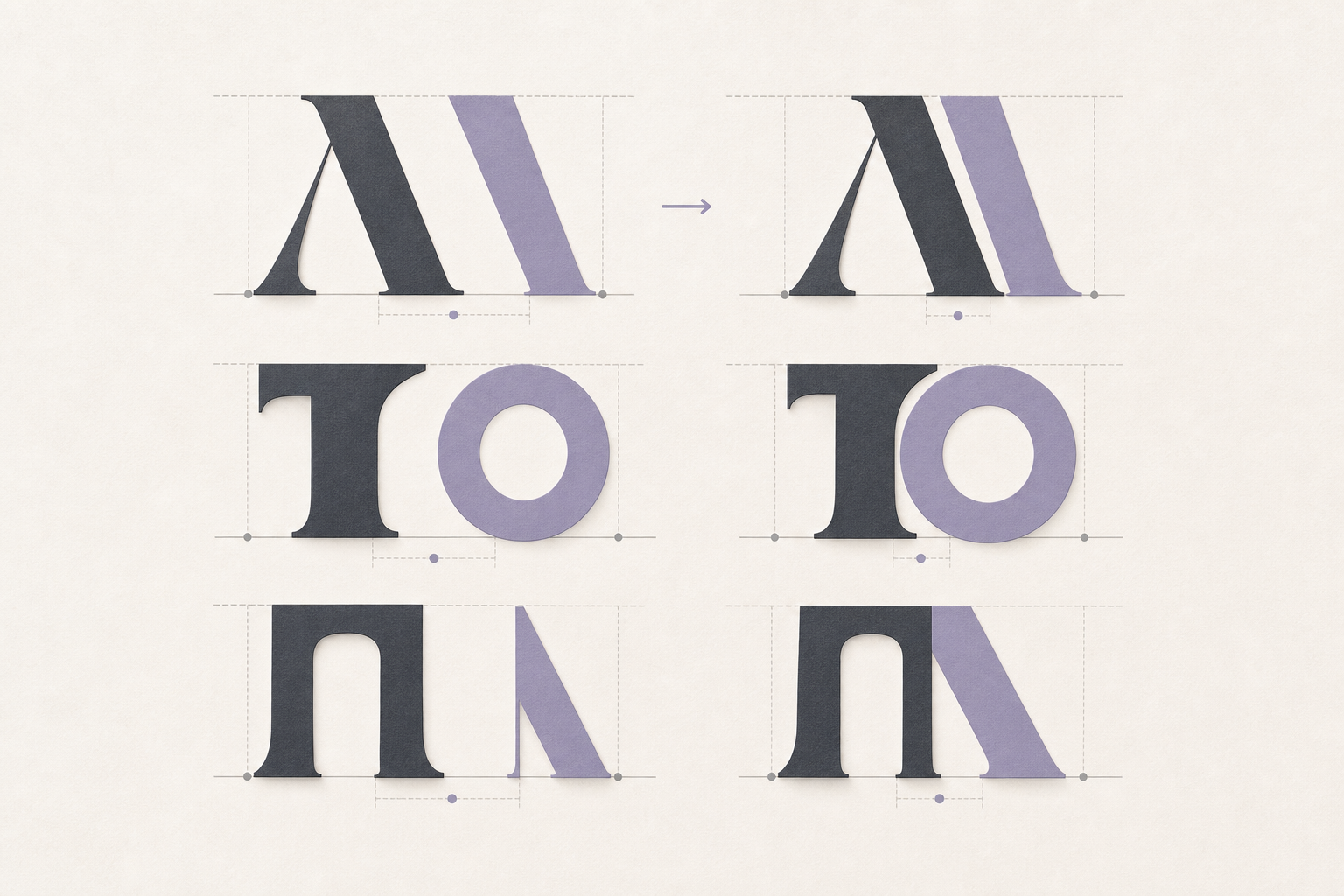
Кернинг — это точечная настройка расстояния между определёнными парами букв, чтобы слово выглядело равномерным и цельным. Он влияет не на смысл текста, а на его ритм, читаемость и визуальный характер. Ниже разберём, как работает кернинг, чем он отличается от трекинга и где ручная настройка особенно важна.
Что такое кернинг в типографике
Кернинг в типографике — это изменение интервала между двумя конкретными символами. Например, диагональная буква А рядом с V может создавать ощущение слишком большого просвета, хотя формальные границы символов расположены корректно. Кернинг уменьшает или увеличивает такой интервал, чтобы зрительно выровнять слово, заголовок или знак.
Главное свойство кернинга — адресность. Он применяется не ко всей строке сразу, а к отдельным сочетаниям: AV, VA, To, Ta, Yo, Wa, ЛА, ТА и другим. В одном слове соседние пары могут требовать разных решений. Поэтому механическое уменьшение расстояния между всеми буквами не заменяет полноценную настройку.
В цифровом шрифте правила кернинга обычно входят в саму шрифтовую систему. При наборе приложение использует пары и значения интервалов, заданные автором гарнитуры. Однако автоматический результат не всегда идеален: он зависит от размера, начертания, языка, рендеринга и конкретной композиции. В крупных надписях дизайнер часто проверяет и корректирует его вручную.
Как кернинг меняет восприятие текста
Читатель редко осознаёт кернинг как отдельный приём, но быстро замечает его последствия. Ровный интервал помогает воспринимать слово как единый визуальный объект. Неравномерный интервал, напротив, создаёт случайные пустоты и слипшиеся участки, из-за чего надпись кажется любительской, даже если выбран хороший шрифт.
Особенно заметен кернинг в коротких словах, крупных заголовках и логотипах. В абзаце мелкого текста глаз воспринимает множество символов одновременно, поэтому небольшие ошибки частично растворяются в общем ритме строки. В слове из четырёх букв любая проблемная пара занимает значительную часть композиции и сразу влияет на баланс.
Кернинг также влияет на эмоциональный тон. Плотная, но аккуратная посадка букв может сделать заголовок энергичным и уверенным. Слишком разреженная надпись воспринимается как дистанционная или декоративная, а случайно слипшиеся символы вызывают ощущение спешки. Это не универсальные правила характера, но визуальный интервал действительно меняет темп чтения и выразительность.
Кернинг, трекинг и межбуквенный интервал: в чём разница
Кернинг и трекинг решают похожую задачу, но работают на разных уровнях. Кернинг корректирует расстояние между конкретной парой символов. Трекинг, или общее межбуквенное расстояние, равномерно меняет интервалы во всём выделенном слове, строке или текстовом блоке. Один инструмент не может полностью заменить другой.
- Кернинг исправляет локальную проблему между двумя символами.
- Трекинг задаёт общий ритм набора и меняет плотность всей строки.
- Интерлиньяж управляет расстоянием между строками и не относится к кернингу.
- Ширина шрифта и его пропорции влияют на восприятие интервалов, но не являются настройкой кернинга.
- Масштабирование текста может сделать прежние интервалы визуально слишком тесными или слишком свободными.
Практический пример: если слово выглядит слишком плотным целиком, сначала проверьте трекинг. Если же почти все буквы сбалансированы, но сочетание Tо или АV выглядит неестественно, нужна точечная коррекция кернинга. Смешивать эти настройки без контроля опасно: после изменения общего интервала отдельные пары могут потребовать повторной проверки.
Почему формы букв создают неравномерные просветы
Интервалы в строке оцениваются не по математическому расстоянию между прямоугольными границами символов, а по видимым просветам. У букв с вертикальными штрихами и у букв с диагоналями, округлыми контурами или выступающими элементами визуальная масса распределена по-разному. Поэтому одинаковые числовые интервалы не гарантируют одинакового зрительного результата.
Пара АV часто требует внимания, потому что диагонали могут образовать заметный треугольный просвет. В сочетании To верхняя перекладина T и округлая форма o дают другой рисунок пустого пространства. У букв Л и А в кириллице также может появляться лишний воздух или, наоборот, ощущение слипания. Решение зависит от конкретного шрифта, размера и соседних знаков.
Где ручная настройка кернинга особенно важна
Автоматического кернинга обычно достаточно для обычного длинного текста, если шрифт хорошо спроектирован и используется в подходящем размере. Ручная настройка становится важнее там, где надпись рассматривают как графический объект: в логотипе, на упаковке, в рекламном заголовке, на обложке, в интерфейсном экране или на навигационной табличке.
- Логотипы и названия брендов, где каждая буква влияет на узнаваемость.
- Крупные заголовки, слоганы и постеры с небольшим количеством текста.
- Монограммы, инициалы и короткие подписи.
- Навигация и интерфейсы, где слово должно быстро считываться на расстоянии.
- Текст, переведённый на другой язык или набранный новым шрифтом.
- Шрифтовые композиции, в которых надпись является главным визуальным элементом.
В основном тексте ручная правка каждой пары обычно не оправдана: она трудоёмка и может нарушить единообразие. Здесь важнее выбрать качественную гарнитуру, проверить поддержку нужного языка, установить комфортный размер и оценить строку в реальном макете. Для дисплейной типографики приоритет меняется: выразительность и оптический баланс становятся частью дизайна.
Как настроить кернинг: практический алгоритм
Настройка кернинга начинается не с отдельных букв, а с оценки всей композиции. Сначала выберите финальный шрифт, начертание, размер и фон. Затем включите автоматический режим, если он доступен, и только после этого переходите к ручным парам. Иначе изменения придётся повторять при каждом изменении гарнитуры или масштаба.
- Наберите слово или фразу в окончательном начертании и размере.
- Отойдите от экрана или уменьшите масштаб, чтобы оценить надпись целиком.
- Найдите места, где просвет заметно больше или меньше соседних интервалов.
- Проверьте проблемную пару в составе всего слова, а не изолированно.
- Изменяйте интервал небольшими шагами и сравнивайте результат до и после.
- Посмотрите надпись на светлом и тёмном фоне, если она будет использоваться в обоих вариантах.
- Проверьте кириллические и латинские символы, цифры, знаки препинания и специальные символы.
- Сохраните итоговую версию и протестируйте её в реальном размере применения.
Для визуальной проверки полезно временно превратить текст в крупную надпись и смотреть не на буквы по отдельности, а на чередование тёмных форм и светлых просветов. Если взгляд постоянно цепляется за одну пару, её стоит проверить. Важно не добиваться одинаковой геометрической дистанции: цель кернинга — одинаковое зрительное ощущение, а не одинаковые числа.
Пример: слово с латинскими буквами AV
Представьте слово с сочетанием AV в крупном капительном наборе. При стандартном интервале между прямоугольными областями букв между диагоналями может остаться слишком широкий просвет. Умеренное сближение пары делает слово плотнее и визуально устойчивее. Если уменьшить расстояние чрезмерно, диагонали начнут восприниматься как единая форма, поэтому результат нужно оценивать в контексте остальных букв.
Пример: кириллические сочетания ЛА и ТА
В кириллице похожая задача возникает у сочетаний с диагональными штрихами. В парах ЛА или ТА просвет может выглядеть иначе, чем между двумя вертикальными буквами. Нельзя автоматически переносить настройки из латинского алфавита: кириллические знаки имеют собственную пластику, а конкретный шрифт может строить их совершенно по-разному.
Кернинг в интерфейсах, логотипах и печати
В интерфейсах кернинг нужно оценивать вместе с адаптивностью. Заголовок, который выглядит аккуратно на широком экране, может переноситься на мобильном устройстве и образовывать новую строку с другим визуальным ритмом. Для коротких кнопок и названий ручная коррекция возможна, но для постоянно меняющегося пользовательского текста лучше опираться на настройки самого шрифта и проверять разные размеры.
В логотипе кернинг становится частью фирменной графики. Здесь допустимы нестандартные решения: отдельные буквы могут быть сближены сильнее, чем требует обычный набор, если это поддерживает силуэт знака. Однако такая свобода требует контроля: слово должно оставаться читаемым, а расстояния между всеми группами символов — выглядеть намеренными.
В печати итог зависит от технологии, материала и масштаба. Тонкие просветы могут выглядеть иначе на экране, на мелованной бумаге, на ткани или на маленькой наклейке. Поэтому крупную типографическую композицию проверяют в предполагаемом физическом размере, а не только в увеличенном масштабе редактора.
Чеклист проверки кернинга перед публикацией
Чеклист помогает не ограничиваться первым впечатлением. Его особенно полезно применять к логотипам, обложкам и крупным заголовкам, где даже небольшая неточность заметна. Проверяйте не только красивый фрагмент в редакторе, но и финальный экспорт: после преобразования, масштабирования или замены формата текст может выглядеть иначе.
- Проверьте строку в финальном шрифте, начертании и размере.
- Оцените интервалы между вертикальными, округлыми и диагональными буквами.
- Просмотрите отдельные пары AV, VA, To, Ta, Wa, ЛА, ТА и похожие сочетания.
- Сравните надпись на расстоянии и в непосредственной близости.
- Убедитесь, что слово читается без случайных слипаний.
- Проверьте разные языки, цифры и знаки препинания, если они нужны в проекте.
- Оцените контраст текста и фона, потому что он меняет заметность просветов.
- Сделайте контрольный просмотр после экспорта и в реальном сценарии использования.
Частые ошибки при работе с межбуквенными интервалами
Одна из распространённых ошибок — путать локальную коррекцию с общим разреживанием. Дизайнер видит одну неудачную пару и увеличивает или уменьшает расстояние у всей строки. В результате проблемное место может исправиться, но остальные интервалы потеряют баланс. Корректируйте только тот участок, который действительно требует вмешательства.
Другая ошибка — оценивать буквы в режиме сильного увеличения и забывать о реальном масштабе. На экране крупный просвет может казаться критичным, хотя в макете он незаметен. Обратная ситуация тоже возможна: небольшая ошибка в логотипе хорошо видна на вывеске. Проверка должна включать несколько масштабов и контекст применения.
Нельзя blindly переносить значения между гарнитурами, начертаниями и алфавитами. Жирное начертание имеет другую плотность, курсив меняет направление и выступы, а кириллица отличается от латиницы формами знаков. Настройки, подходящие для одного шрифта, не являются универсальным стандартом для другого.
- Не исправляйте каждую пару без визуальной причины.
- Не делайте все интервалы одинаковыми по числовому значению.
- Не проверяйте только одну букву или изолированную пару.
- Не используйте слишком плотный набор ради компактности.
- Не переносите латинские настройки на кириллицу автоматически.
- Не забывайте о переносах, адаптивных размерах и финальном носителе.
Часто задаваемые вопросы о кернинге
Что такое кернинг простыми словами?
Кернинг — это настройка расстояния между двумя соседними буквами, чтобы они выглядели ровно и гармонично. Например, диагональные или округлые формы могут создавать лишний просвет. Кернинг исправляет именно такую локальную особенность, а не меняет расстояние между всеми символами текста.
Чем кернинг отличается от трекинга?
Кернинг применяется к отдельным парам букв, а трекинг равномерно меняет межбуквенное расстояние во всём выделенном фрагменте. Кернинг исправляет локальный дисбаланс, трекинг управляет общей плотностью набора. В одной надписи могут использоваться оба инструмента, но они отвечают за разные уровни типографической настройки.
Нужно ли настраивать кернинг в обычном тексте?
Обычно в основном тексте достаточно автоматического кернинга, встроенного в качественный шрифт. Ручная настройка оправдана для крупных заголовков, логотипов, коротких подписей и других заметных композиций. В длинном наборе важнее стабильность, удобный размер, интерлиньяж и корректная работа шрифта с нужным языком.
Почему в логотипе кернинг заметнее, чем в статье?
Логотип часто состоит из одного короткого слова, которое воспринимается как единый знак. Поэтому одна неравномерная пара занимает заметную долю всей композиции. В длинном абзаце внимание распределяется между множеством символов, и небольшие отклонения обычно не так сильно влияют на общее впечатление.
Можно ли исправить кернинг в любом редакторе?
Да, большинство графических и текстовых редакторов позволяют менять межбуквенный интервал хотя бы на уровне выделенного фрагмента. Возможности различаются: где-то доступен общий трекинг, а где-то можно задать точечный кернинг между отдельными символами. Для логотипов и сложных композиций также используют векторные инструменты, где буквы можно преобразовать в контуры.
Как понять, что кернинг настроен правильно?
Правильный кернинг не привлекает внимание к отдельным промежуткам: слово воспринимается цельно, а светлые просветы выглядят уравновешенными. Проверяйте надпись в контексте, на рабочем размере и с предполагаемым фоном. Если после коррекции взгляд перестаёт цепляться за конкретную пару, настройка, вероятно, стала точнее.
Вывод: кернинг как инструмент визуальной точности
Кернинг помогает управлять не содержанием, а тем, как текст выглядит и читается. Он выравнивает зрительные просветы, усиливает аккуратность заголовков и делает логотипы цельными. Для большинства абзацев достаточно хорошего автоматического набора, но в крупных и брендовых надписях ручная проверка часто становится обязательной частью работы.